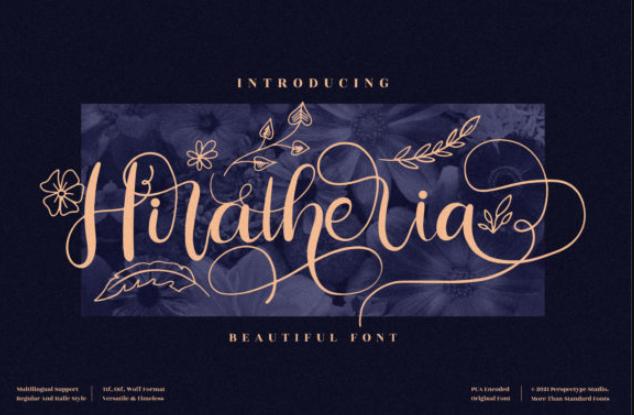
[Creativefabrica] Hiratheria Font (perspectype)
Hiratheria - восхитительный скриптовый шрифт. Этот шрифт аккуратно обработан и очень детализирован. Какой бы ни была тема, этот шрифт станет прекрасным дополнением к вашей библиотеке шрифтов, поскольку он может улучшить любое творение.